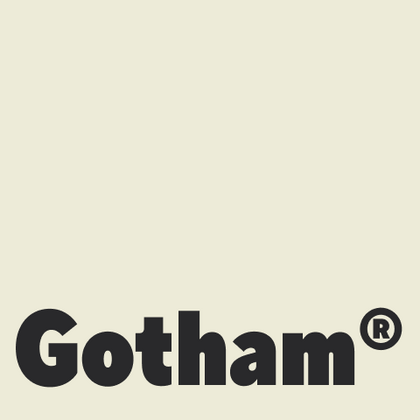
Ähnliche Schriftarten wie Gotham
Gotham® ist ein Klassiker, aber nicht die einzige Option. In der TypeType-Kollektion finden Sie interessante Alternativen mit modernen Proportionen und durchdachter Typografie. Unsere Schriften bewahren die klare Geometrie von Gotham®, bieten jedoch eine verbesserte Lesbarkeit in kleinen Größen und mehr stilistische Variationen. Für diejenigen, die über Standardlösungen hinausgehen möchten, haben wir eine Auswahl an Schriftarten vorbereitet, die in denselben Bereichen (Branding, Benutzeroberflächen, Werbung) funktionieren, aber frisch und unkonventionell wirken.
Wenn Sie genug haben von “abgedroschenen” Schriften und auf der Suche nach einer Kopfzeile ähnlich wie Gotham sind, sehen Sie sich unsere besten Alternativen zu Gotham an. Das sind Schriftarten, die ähnliche Eigenschaften haben, aber gleichzeitig neue und einzigartige Designmerkmale aufweisen. Sie gehören z. B. zur gleichen Schriftkategorie, eignen sich für die gleichen Zwecke und haben ähnliche Merkmale, unterscheiden sich aber in Details oder Proportionen.
Bei TypeType finden Sie topaktuelle Schriftarten wie Gotham und noch besser: hier sind einige großartige und nicht so gängige Alternativen zu Gotham. Nutzen Sie diese Liste hochwertiger, an Gotham erinnernder Schriften nach Ihrem Geschmack. Auf diese Weise können Sie eine noch passendere Schriftart für Ihr Projekt finden, Ihre Auswahl erweitern oder Ihr Design auffrischen. Alle Schriften in dieser Sammlung sind in verschiedenen Formaten und zu erschwinglichen Preisen erhältlich, so dass Sie für jeden Bedarf eine passende Schrift finden werden!
Finden Sie einen großartigen Ersatz für Gotham und versuchen Sie, eine ähnliche Stimmung zu imitieren und das gewünschte Gefühl zu vermitteln, indem Sie sie in Ihren Designs verwenden. Jede auf dieser Seite vorgestellte Schriftart ist ein Zwilling der Schriftart Gotham, und zwar ihr vollständiges Analog.